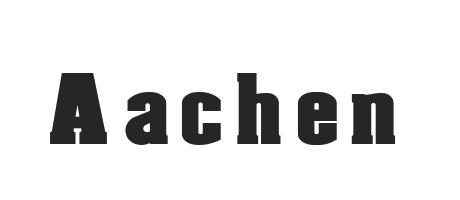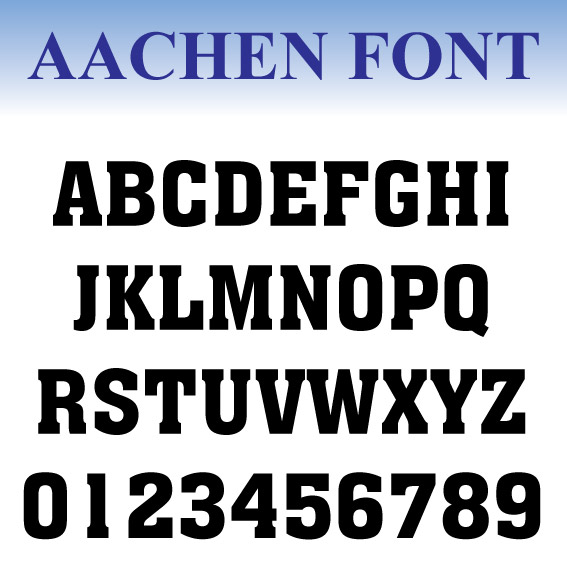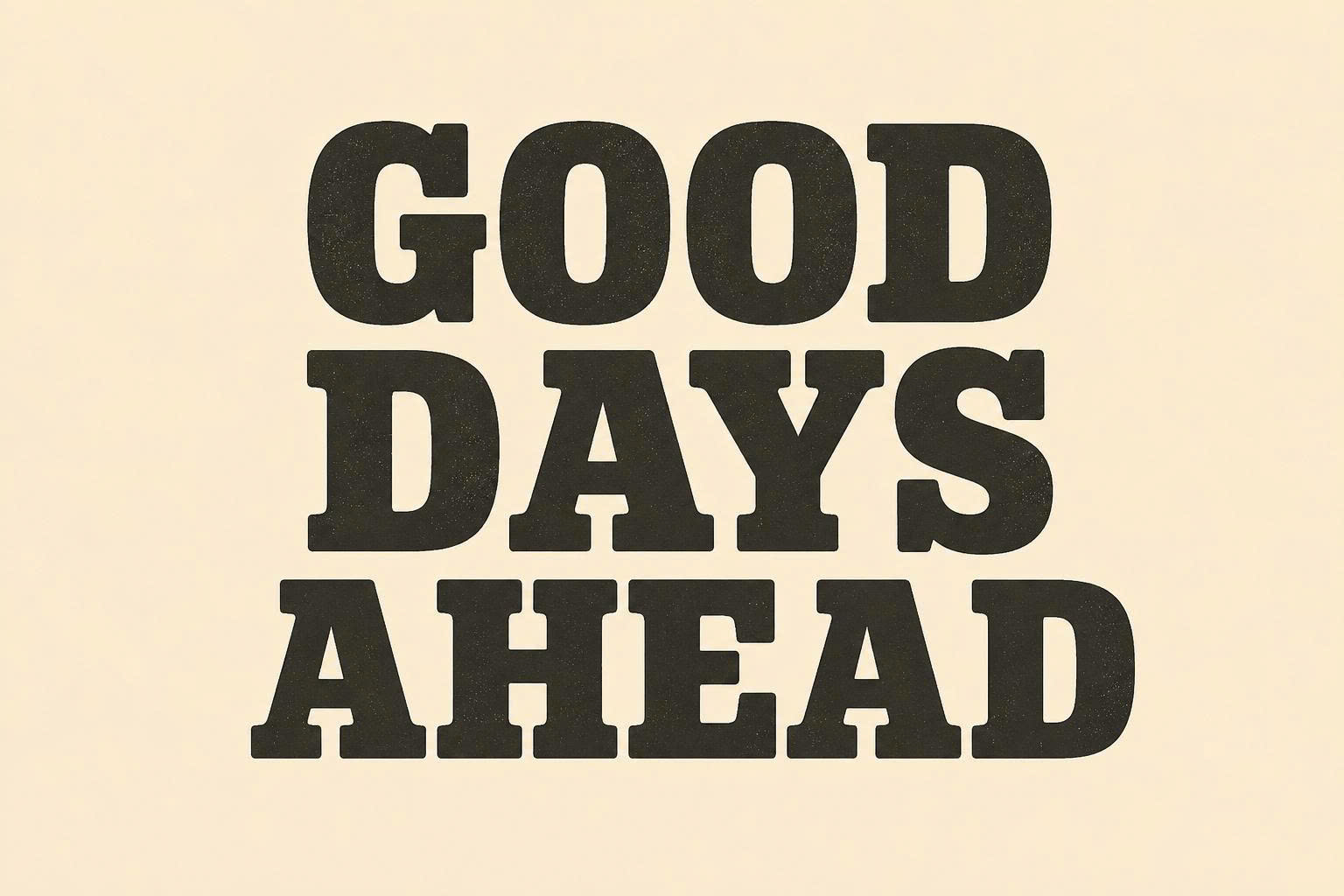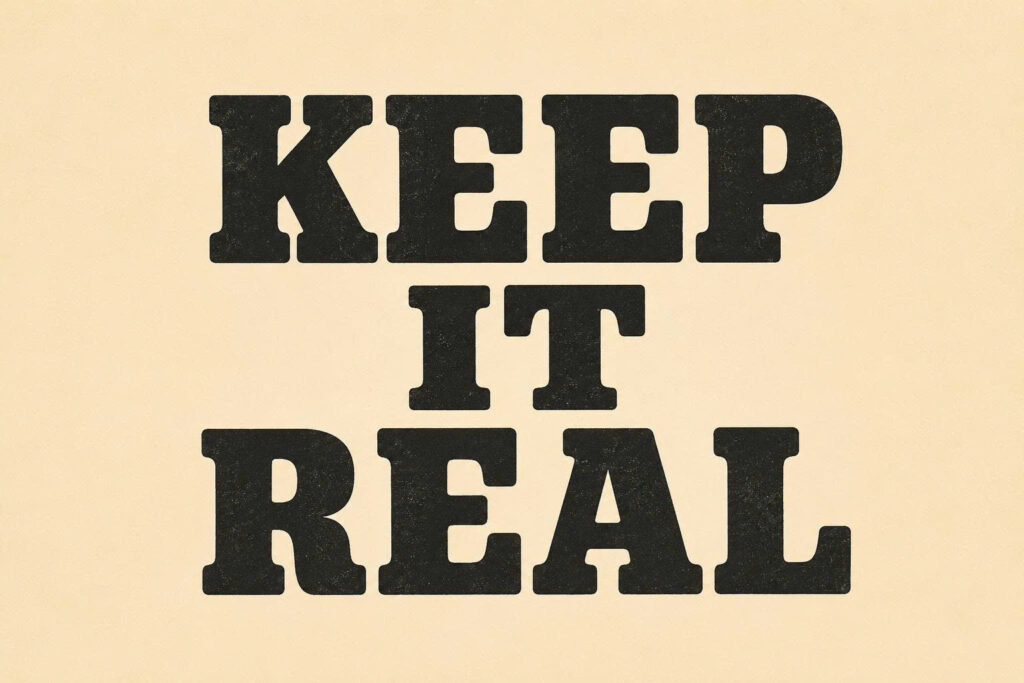
Font Aachen Việt hóa là bộ phông chữ thuộc dòng Heavy Slab Serif kinh điển do Colin Brignall thiết kế cho hãng Letraset vào năm 1969, nổi tiếng với các khối chân chữ vuông vức , tỷ lệ hình thể cơ bắp và độ dày nét áp đảo. Mang vẻ ngoài kiên cố, đanh thép và đậm chất cơ khí công nghiệp, font Aachen Bold Việt hóa là chất liệu trực quan tuyệt vời để các kiến trúc sư, kỹ sư kết cấu tạo dựng sự vững vàng cho các bản vẽ phối cảnh nhà xưởng tiền chế, xưởng cơ khí container hay hệ thống biển hiệu câu lạc bộ thể hình.
Khối hình cơ bắp và chân chữ vuông vức kiên cố của font Aachen Việt hóa
Điểm cuốn hút của font Aachen Việt hóa nằm ở cấu trúc chữ đầm chắc như những khối đúc bằng gang thép, nơi các đường chân chữ ngắn dày dặn kết hợp cùng thân chữ đặc kín tạo nên một bệ đỡ thị giác vô cùng vững chãi. Tỷ lệ ký tự sở hữu độ mở rộng hào phóng, các nét cong được gọt vát hình học mang lại nhịp điệu dứt khoát, loại bỏ hoàn toàn sự yếu ớt hay rườm rà của các phông chữ trang trí thông thường.
Sự ổn định về mặt thị giác của dòng font này giúp khẳng định sức mạnh kết cấu, tính bền bỉ và tinh thần lao động bền bỉ của đơn vị chủ trì công trình. Khi xuất hiện trên các bề mặt vật liệu kiến trúc hiện đại như tấm thép gân chống trượt, vách tôn sóng container sơn màu xám khói, khung dầm chữ I hay bê tông trần, Aachen tạo nên sự đồng điệu thẩm mỹ cơ khí đầy uy lực.
| Phân loại phong cách | Heavy Slab Serif / Industrial Egyptian / Athletic Display |
| Mục đích phù hợp | Biển hiệu nhà xưởng, tiêu đề bản vẽ CAD, logo thể thao |
03 Ứng dụng font Aachen Bold Việt hóa vào công trình thực tế
Nhờ vẻ ngoài khỏe khoắn và tính gợi hình cơ bắp mạnh mẽ, bộ phông chữ này mang lại giá trị thực tế lớn trong khâu tạo điểm nhấn cho các công trình hiện đại:
- Biển hiệu cho Xưởng Cơ khí và Kho bãi Container: Những khối chữ vuông vức của font Aachen Bold Việt hóa rất ăn ý khi gia công chữ nổi bằng thép tấm hàn thô hoặc sơn stencil trên nền tôn sóng kim loại, mang lại diện mạo đanh thép và thể hiện quy mô sản xuất vững mạnh.
- Hệ thống nhận diện cho Phòng Gym và Câu lạc bộ Thể hình: Phông chữ này khi in trên các tấm cao su chịu lực hoặc bảng alu đen mờ sẽ giúp không gian phòng tập lắp ghép toát lên tinh thần thể thao cuồng nhiệt, tạo động lực rèn luyện cho các hội viên.
- Bìa hồ sơ giải pháp kết cấu thép công trình nặng: Sử dụng font Aachen Việt hóa cho tên dự án và mã hiệu tập bản vẽ giúp hồ sơ toát lên vẻ quy chuẩn, tạo niềm tin lớn với các kỹ sư thẩm tra và chủ đầu tư.
03 Lưu ý bố cục font Aachen giữ trọn uy lực thị giác đanh thép
Để khai thác hiệu quả vẻ đẹp của dòng font Slab Serif nặng ký này mà không gây cảm giác ngột ngạt cho bản vẽ, người thiết kế nên lưu tâm một số kinh nghiệm sau:
- Chừa khoảng thở rộng rãi: Do cấu trúc chân chữ dày và thân chữ nở to, bạn nên bố trí khoảng trống xung quanh tiêu đề thoáng đãng để các khối chữ không bị chèn ép bởi các chi tiết đồ họa phụ trợ.
- Tránh sử dụng cho đoạn văn dài: Độ đậm đặc của Aachen được tối ưu cho các cụm từ ngắn từ 2 đến 5 từ. Việc lạm dụng cho các đoạn văn bản giải thích chi tiết sẽ làm giảm đáng kể tốc độ đọc hiểu của người xem.
- Lựa chọn gam màu công nghiệp dứt khoát: Aachen phát huy hiệu quả thị giác cao khi phối cùng các tông màu mang tính cơ khí như vàng cảnh báo, cam đất, đen tuyền, xám sắt thép hoặc trắng tuyền trên nền tối mờ.